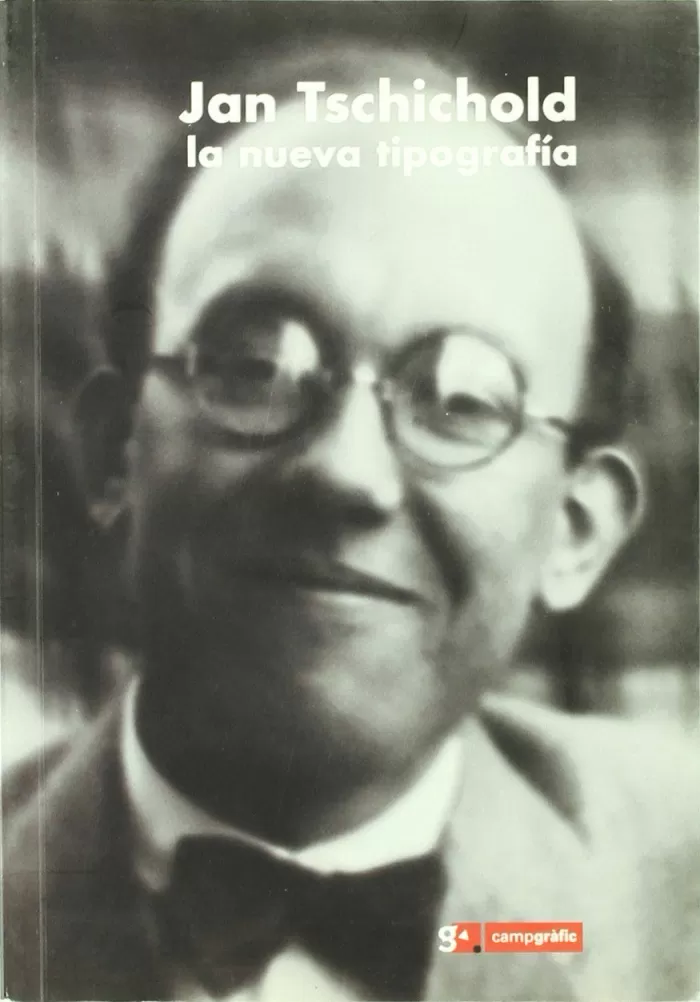
LA NUEVA TIPOGRAFÍA
MANUAL PARA DISEÑADORES MODERNOS
TSCHICHOLD, JAN
LA NUEVA TIPOGRAFÍA
La obra fundamental del pensamiento tipográfico del siglo xx, publicada en Berlín el año 1928. Su propósito es demostrar su relación con todas las áreas de la creatividad y explicar sus consecuencias, exponer con claridad los fundamentos de la tipografía y exigir la
creación de un estilo contemporáneo.